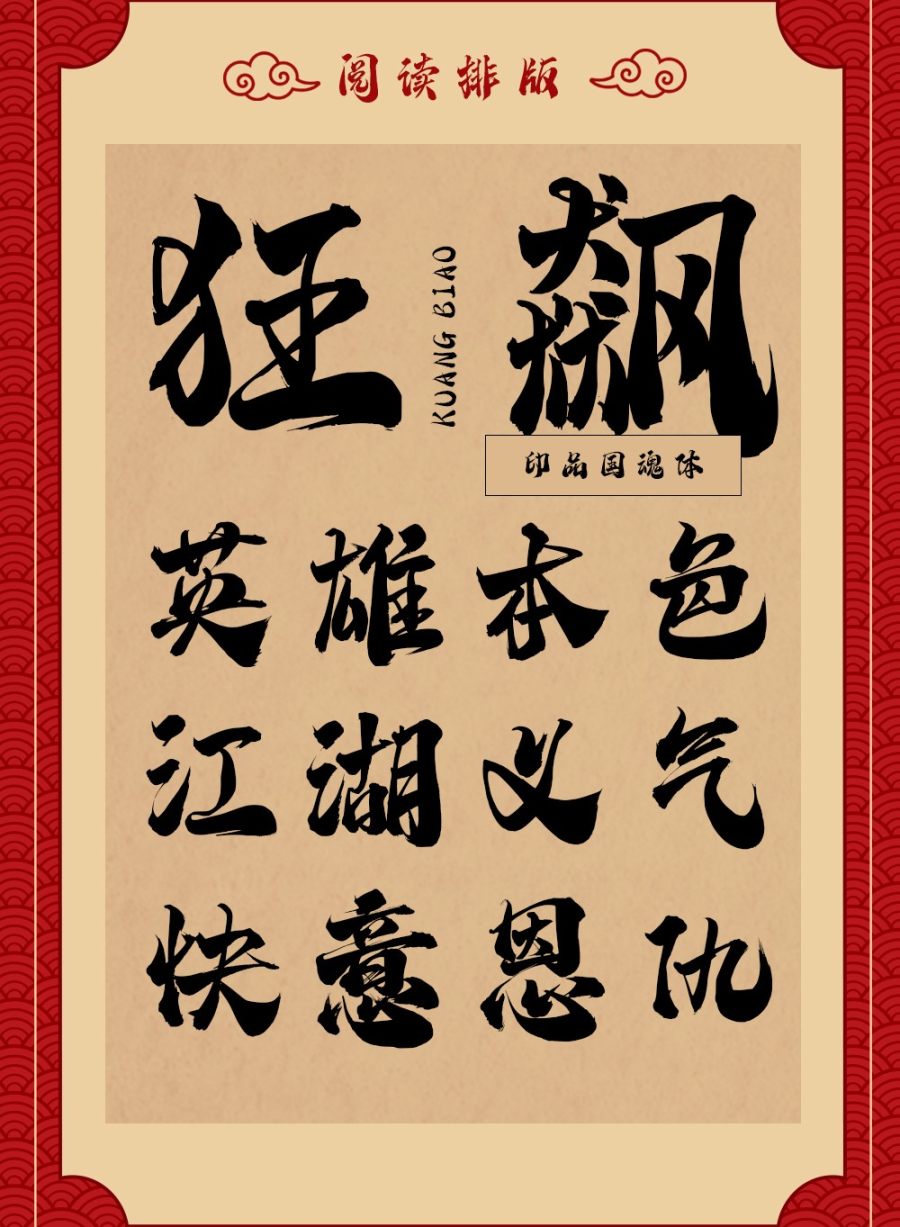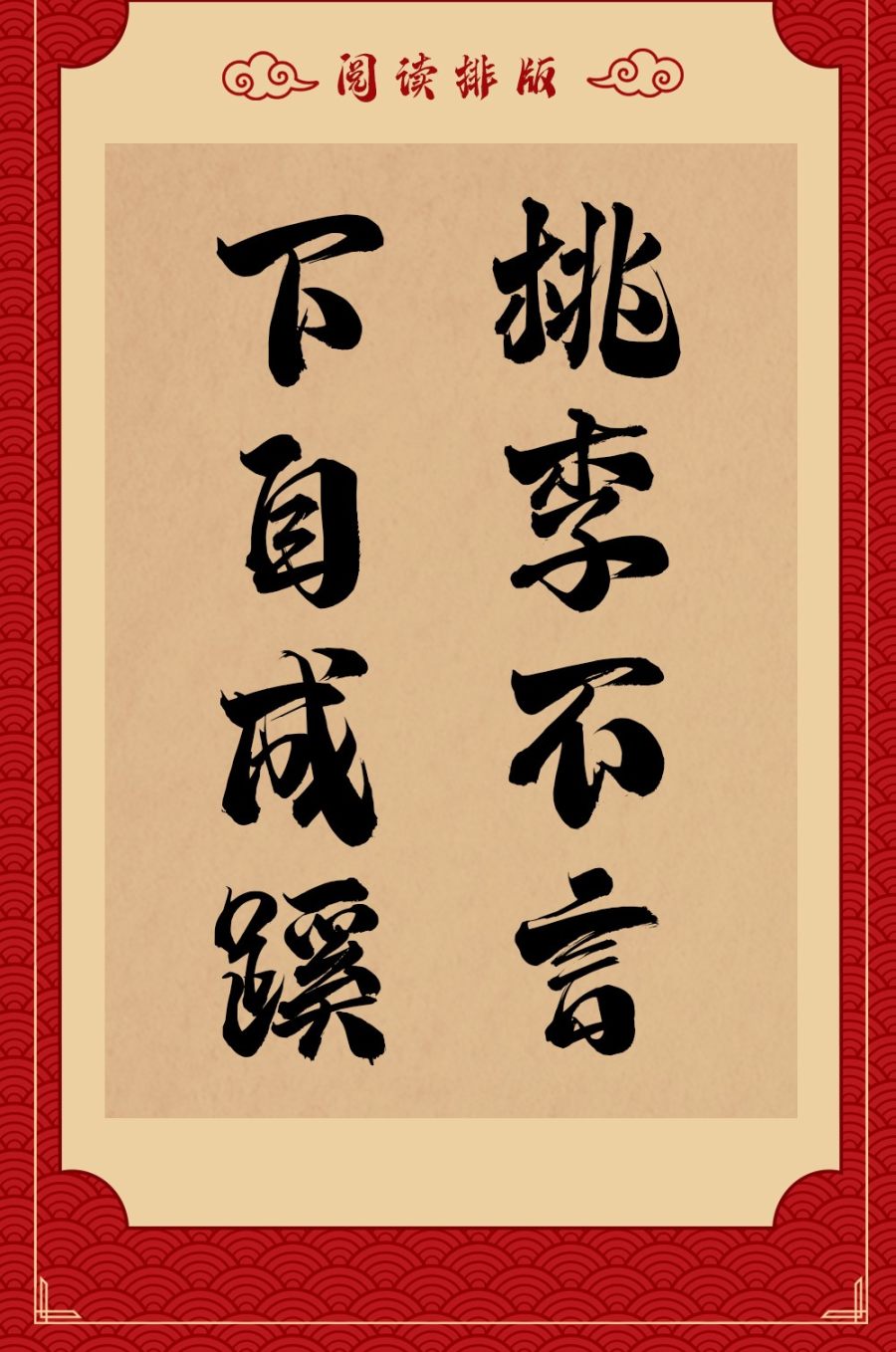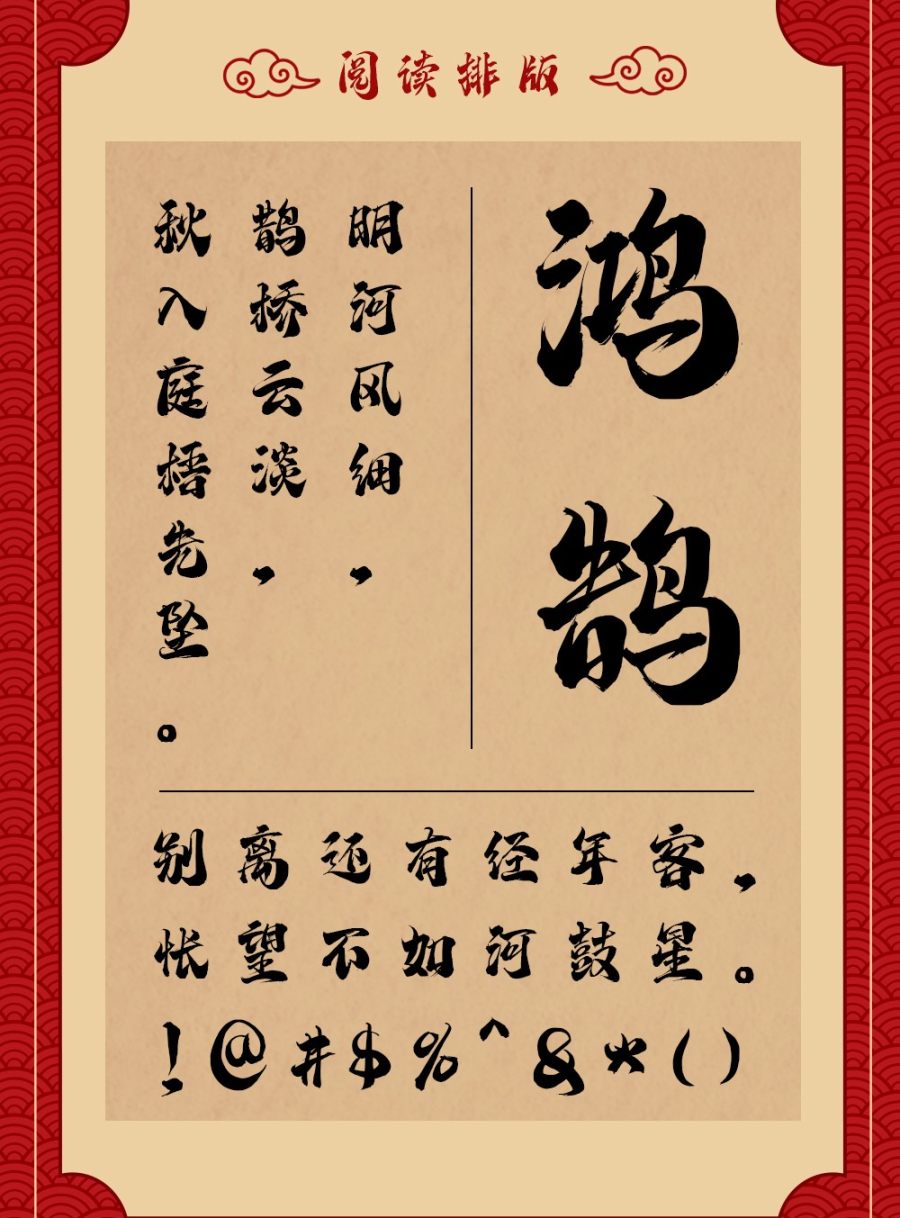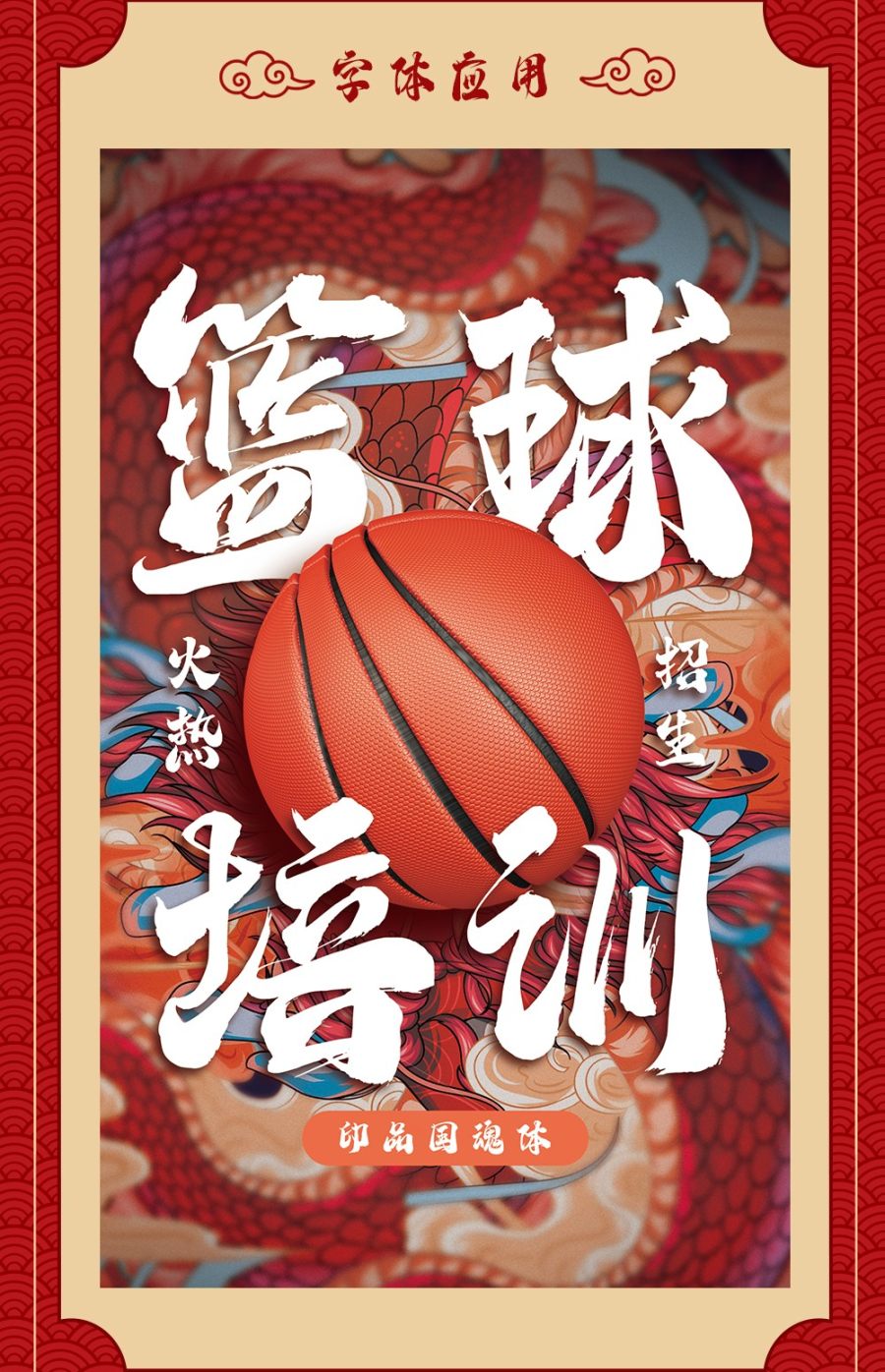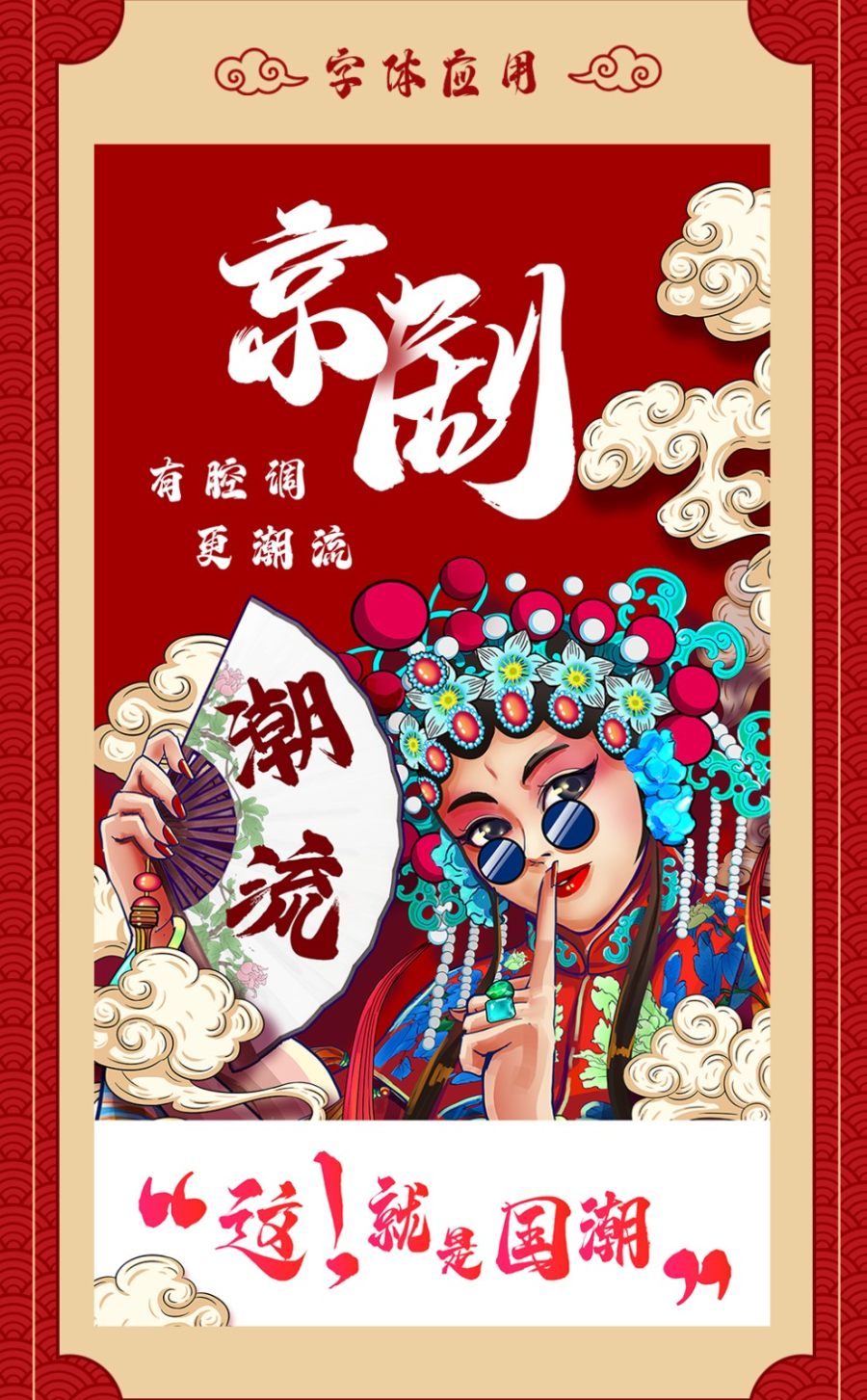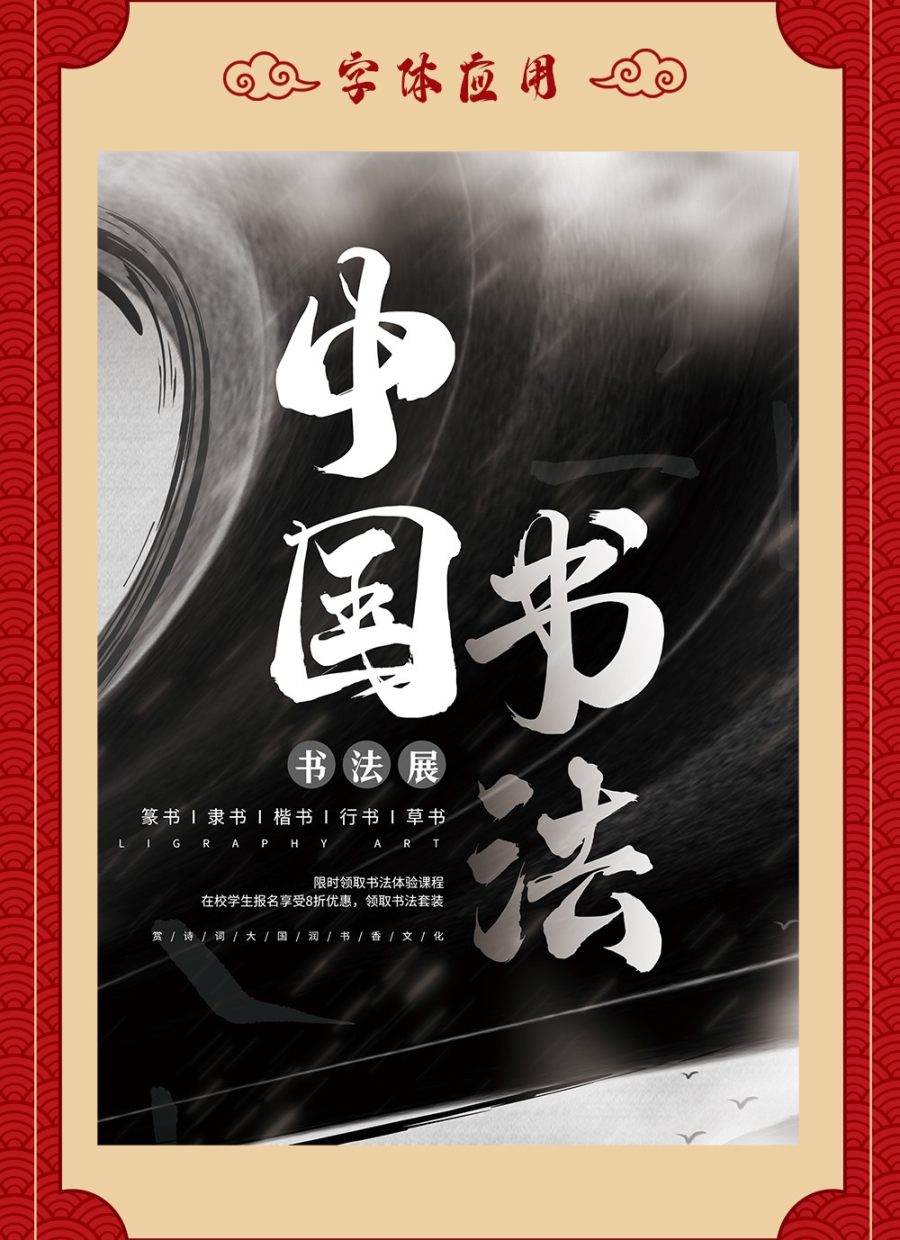
近年来,随着中国文化的复兴,越来越多的人开始喜欢并重视毛笔艺术字。而要想创作出一份优美的毛笔字作品,选用一款好的字体是至关重要的。今天,小编就要向大家介绍一款优秀的毛笔字库——印品国魂体。
印品国魂体的字体笔画有以下几个特点:
首先,印品国魂体的笔画非常自然流畅,每一笔之间都有着很好的连贯性,使得整个字体看起来非常和谐。不会显得生硬、僵硬。
其次,印品国魂体的笔画粗细变化也非常自然,不会像一些毛笔字库那样过于单调,而是更加逼真地还原了毛笔的特点。
最后,印品国魂体的字体具有很好的可读性,无论是大篇幅的文章还是小字体的标语,都能够清晰地表达出来,使得人们更容易读懂文字。
总之,印品国魂体是一款非常优秀的毛笔字库,它不仅具有自然、流畅的笔画特点,还能够很好地还原毛笔的特点,适用于多个应用场景。如果你是一位书法爱好者,或者需要在设计、文学等领域中使用毛笔字,不妨尝试一下印品国魂体,相信它会为你带来不一样的体验。